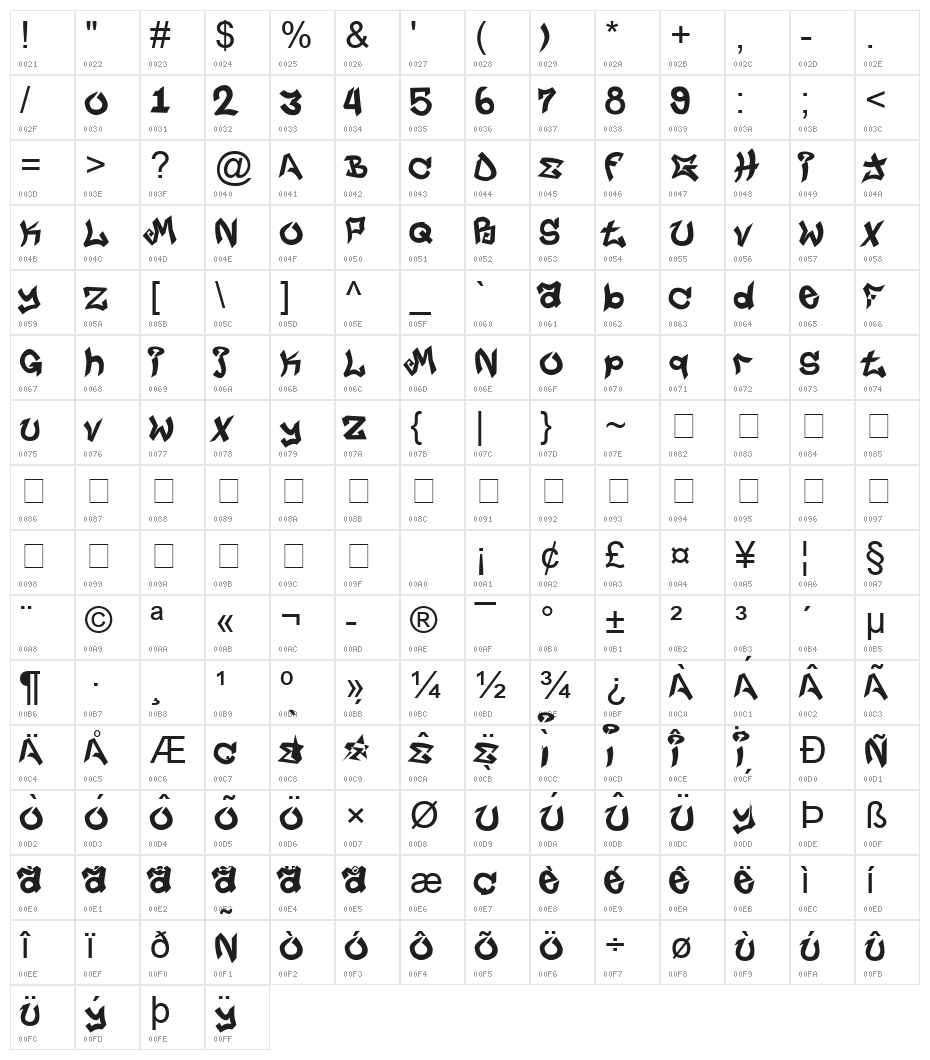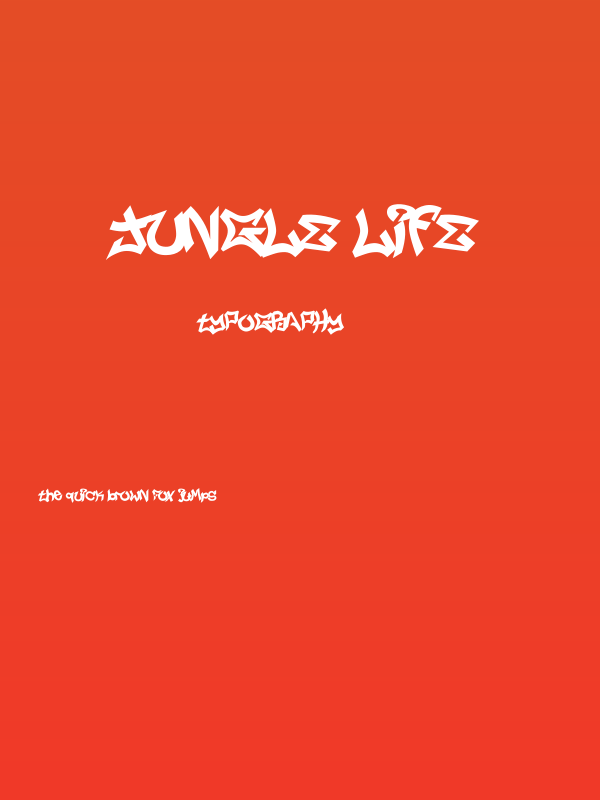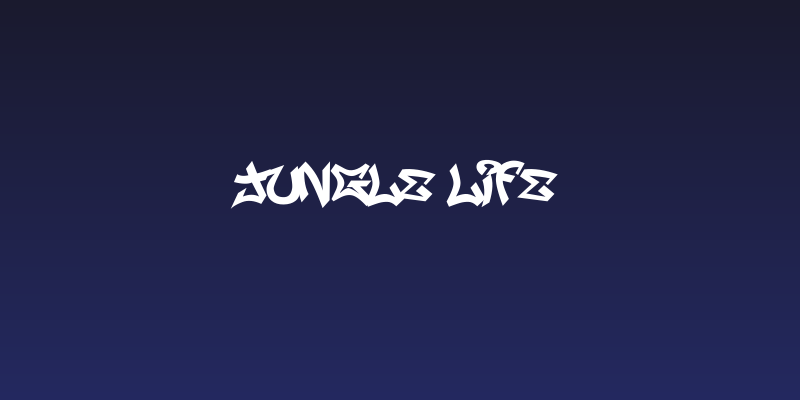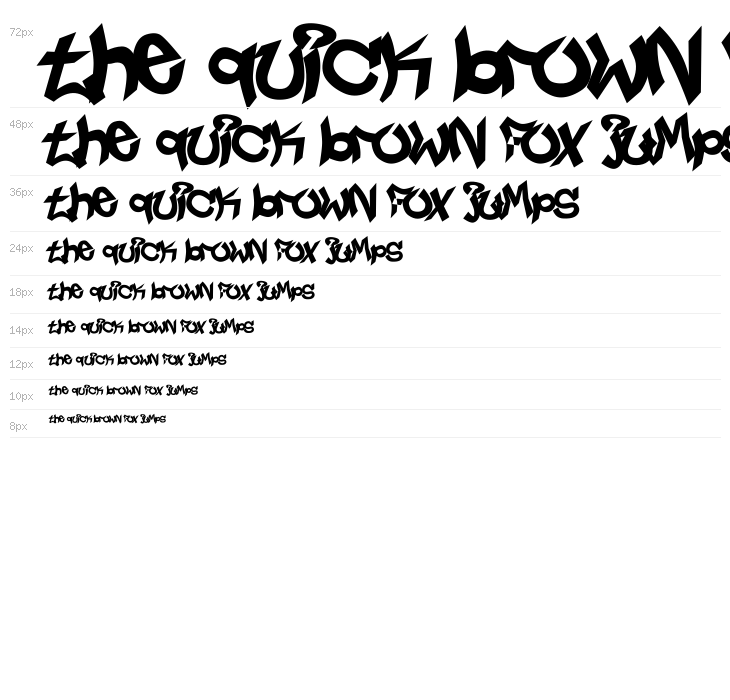
Jungle LIFE Font
| Gesamtstil | Urban, Edgy, Modern |
| Vorgeschlagene Projekte | Perfect for street art designs, urban-themed posters, music album covers, and edgy branding projects. |